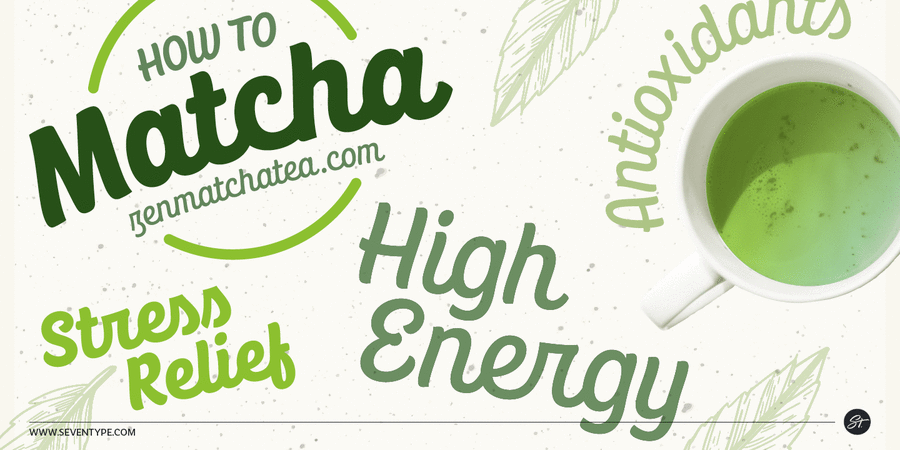
Опис гарнітури CoolKidsНа створення шрифту CoolKids нас надихнула пісня «Signs of Life» гурту Arcade Fire. Через те, що в пісні йдеться про крутих дітей, ми замислилися який би міг мати вигляд шрифт з такою назвою. Ми відразу зрозуміли, що він повинен бути розслабленим і водночас рішучим, виділятися з натовпу.
Після створення жирного накреслення ми вирішили додати світлу, звичайну та середню насиченості, щоб розширити можливості для вашого дизайну.
Шрифт має початкові та кінцеві альтернативні гліфи, які з'являються автоматично. Це надає шрифту природнішого вигляду, робить його подібним до рукописного.
Кожний символ був дбайливо намальований, а з'єднання справді м'які й плавні. Це шрифтове сімейство підтримує більшость мов, що використовують латинку. Як в основних, так і альтернативних формах. CoolKids чудово підходить для створення логотипів, пакування, постерів і багато чого іншого.
Шрифт розробили Луіс Бандовас та Віторія Невес у 2019 році.
Асоціації з сімейством шрифтів CoolKidsОсобистість і характер гарнітури:
тонкий, легкий, делікатний, смачний, соковитий, доброзичливий, здоровий, гнучкий, модний, грайливий, привітний, гладенький, красивий, святковий, свіжий, літній, М'який, солодкий, ввічливий, чистий, якісний, культурний, гармонійний, оригінальний, пластичний, динамічний, приємний, затишний, комфортний, зрозумілий, акуратний, теплий, ясний, природний, натуральний, прикольний, радісний, дитячий, милий, домашній, щасливий, симпатичний, крафтовий, рослинний, ледачий, апетитний, сімейний, хіпстерський, ремісничий, чесний, рукотворний, ручний, екологічний, довірчий, зелений, ламповий, характерний, мотузковий, артізанальний, спекотливий, тропічний, яскравий, виразний, помітний, мультяшний
відпочинок, кафе, смузі, ресторан, краса, селфі, лосьйон, шампунь, здоров'я, преміум, готель, гігієна, чистота, чай, квіти, фломастери, природа, літо, молоко, сніданок, дієта, дитяча книжка, школа, табір, іграшка, гра, зоомагазин, тварини, мультфільм, море, канікули, Хюґе, Інстаграм, графіка, ілюстрація, учень, школяр, дім, ранок, світанок, велнес, їжа, закуска, пляж, одяг, соус, кетчуп, фаст фуд, торгівля, шоколад, родина, магазин, продукти, ремесло, хенд мейд, крамниця, фермер, розваги, свято, подарунки, торт, чіпси, сир, шаурма, лобстер, десерт, піцца, зоопарк, булочна, кава, кондитер, булочка, солодощі, лікер, коктейль, обід, бар, фарба, цукерки, сік, виставка, мафін, кондитерська, морозиво, випічка, жуйка, підгузок Гарнітура асоціюється з віком: